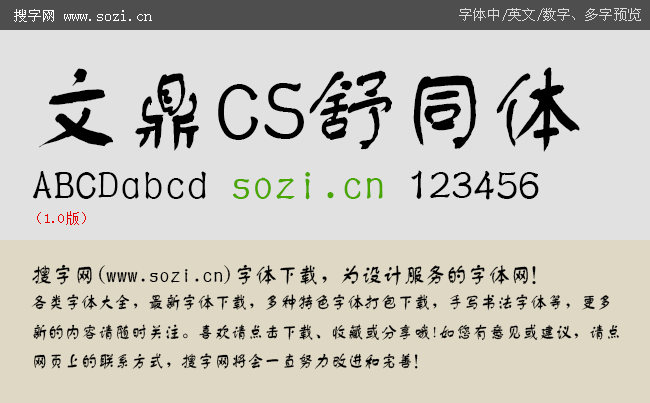
文鼎CS舒同體
搜字網(wǎng)給大家提供一款書法風(fēng)格的文鼎CS舒同體下載。舒同體是被毛澤東主席贊為“紅軍書法家、黨內(nèi)一枝筆”的原中共山東省委第一書記,中國書法家協(xié)會(huì)第一任主席舒同的書法,漢儀舒同體結(jié)體上楷、行、草、篆、隸五體各取一分,風(fēng)格上顏、柳各取一分,何紹基取半分,合稱“七分半”。字體寬博端莊,圓勁婉通,用筆老重,藏頭護(hù)尾,點(diǎn)劃潤厚通暢。此款字體適用于報(bào)紙、刊物、電影、電視等環(huán)境。